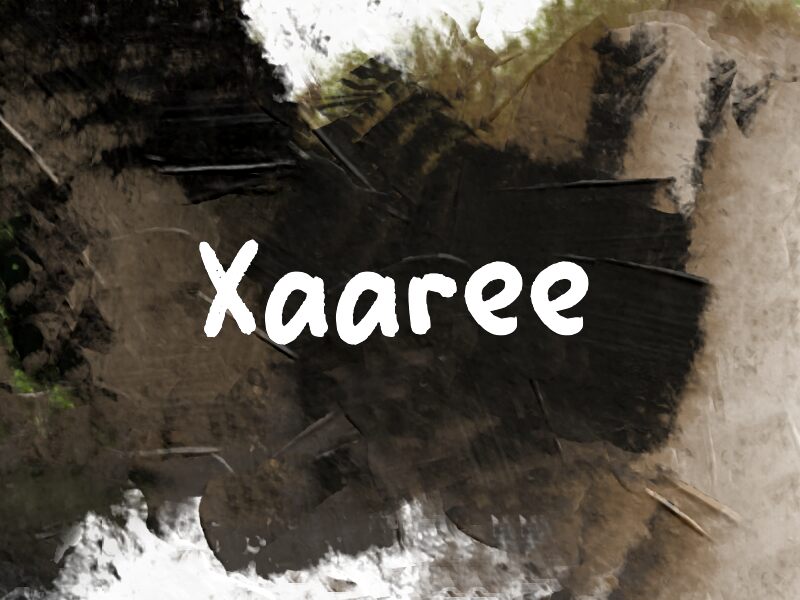
Xaaree
Xaaree di Wep è un font brush gratuito e graffiante, con l'energia dei manifesti dipinti a mano in strada. Le lettere appaiono spesse, secche e leggermente sfrangiate ai bordi, con forme arrotondate e una pressione irregolare che mantiene la texture viva invece che troppo pulita.
Si adatta perfettamente a grafiche musicali, branding di locali, packaging indie, volantini per eventi e titoli d'impatto sui social, dove un font gratuito con il vero carattere del pennello risulta più umano rispetto a uno script troppo perfetto. Usalo per titoli brevi, testi di copertina, bozze di loghi o parole che hanno bisogno di un tocco dipinto rapidamente: i tratti larghi e le curve decise sembrano più le tracce di un pennello carico di colore che lettere rifinite con cura.